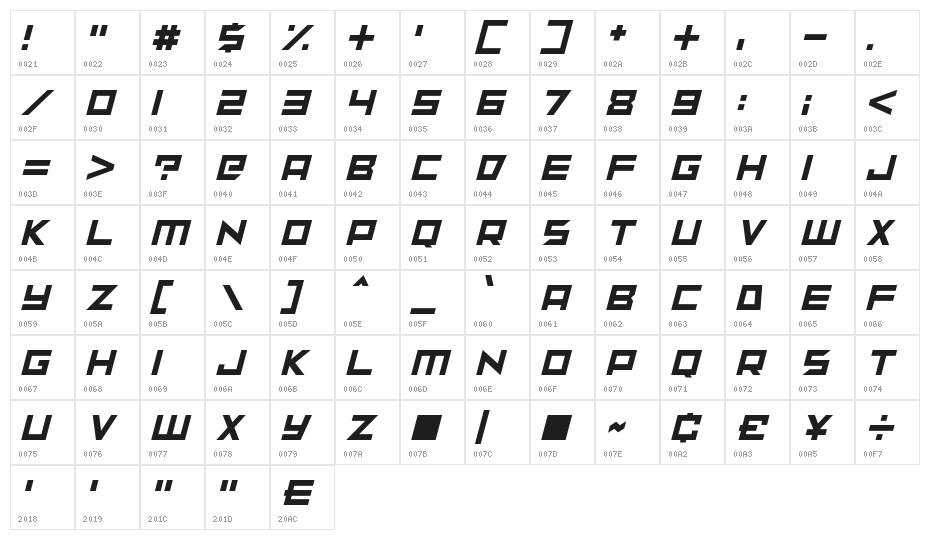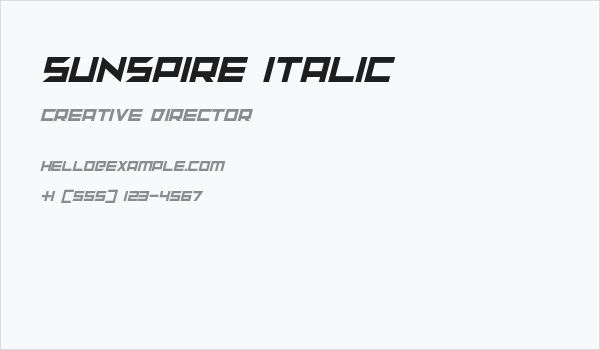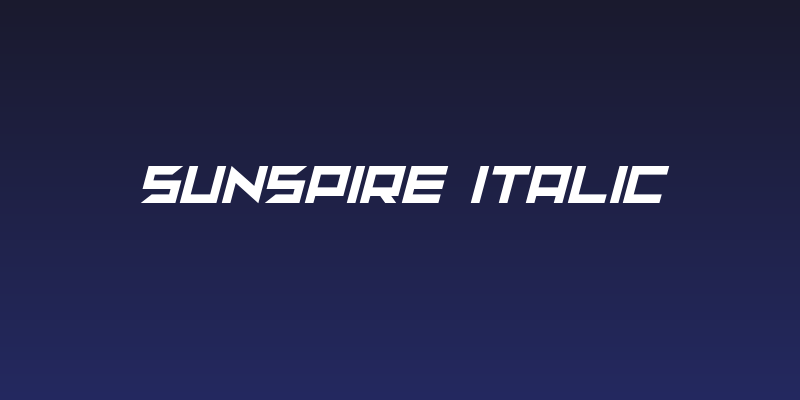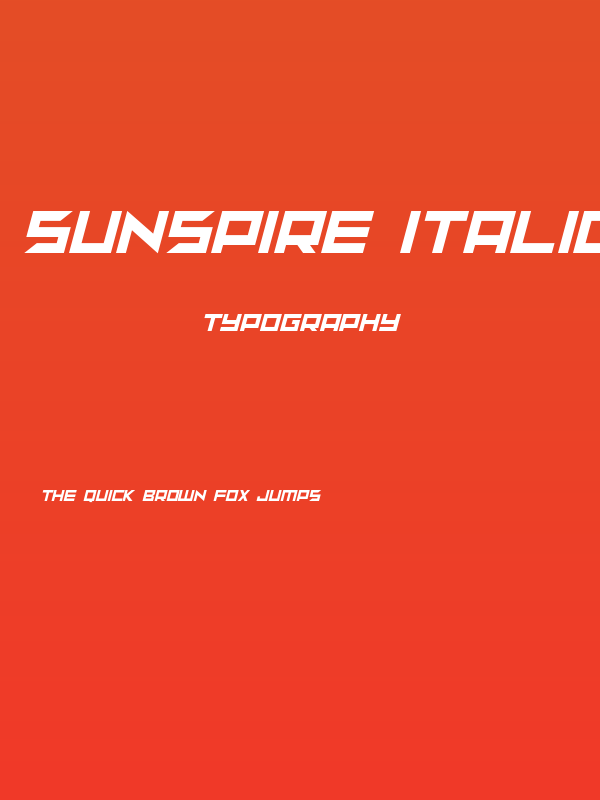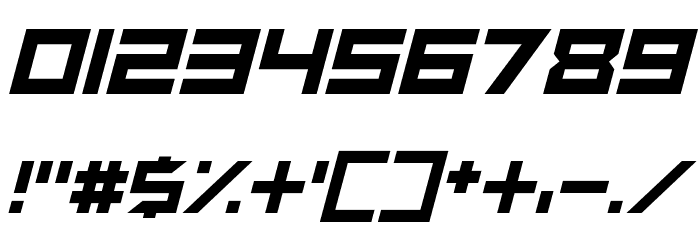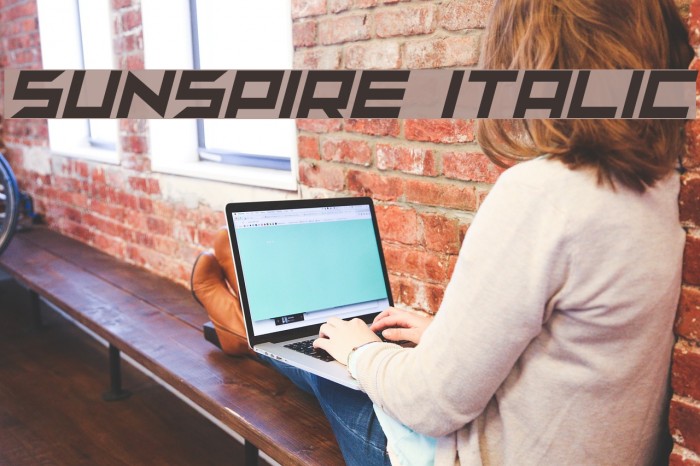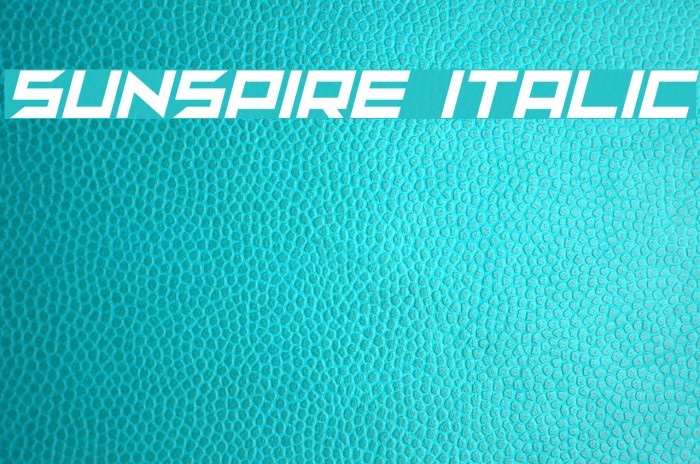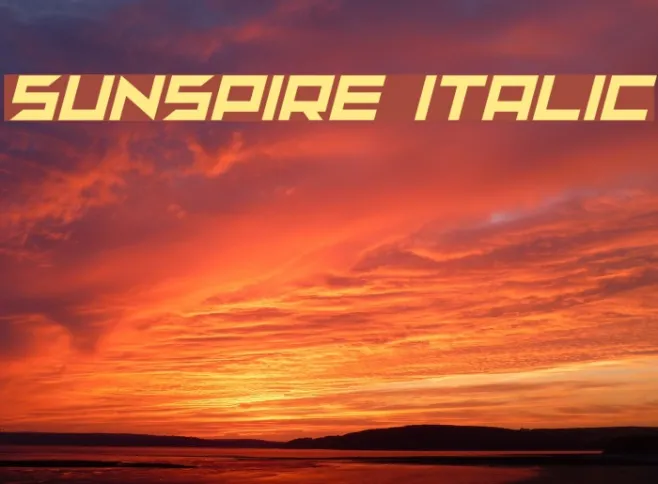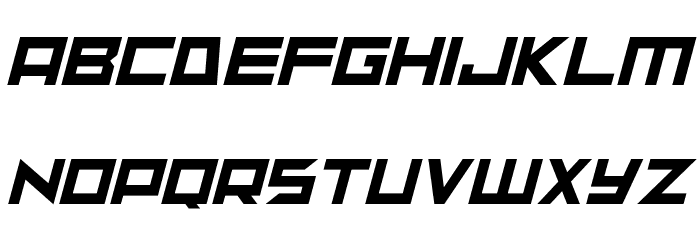
sunspire Italic Font
Darrell Flood
| Proyectos propuestos | Ideal for futuristic branding, sports team logos, tech-related advertisements, and dynamic poster designs. |